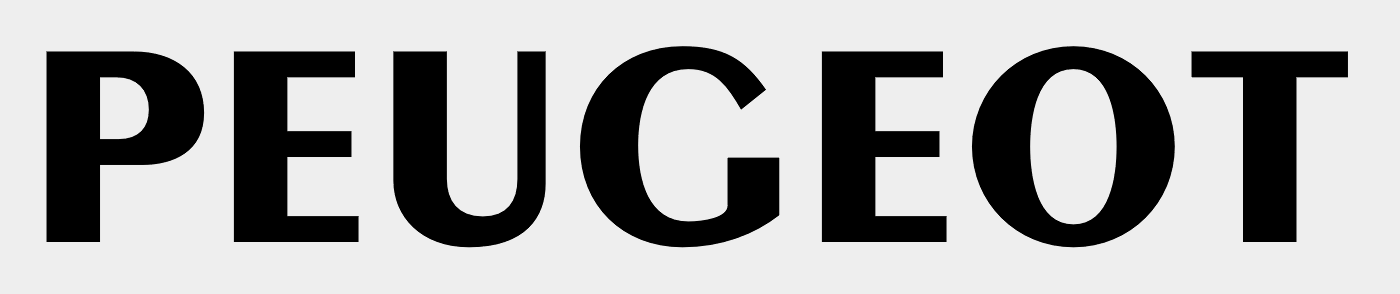
alte Peugeot-Schrift
bin neu hier. Suche diese bestimmte Schriftart, oder zumindest etwas sehr ähnliches.
vielen Dank für den Link. Mache gerade ein Hintergrundbild und ne Navigation für mein TZablet, welches ich in mein Peugeot einbauen möchte. Da kommt das genau richtig. Hatte im Netzt zwar was gefunden, aber die Quali war nicht so gut. Kann ich also gut verwenden. Hab aber leider die Schriftart noch nicht gefunden, die dem Logo ähnelt. Wäre ja schön, wenn die zu dem Logo passen würde.
Und generell wirst du wohl (noch ;-) ) kaum die genaue Schrift finden, denn diese 6 verschiedenen Buchstaben hat der Gestalter des Logos nicht aus einer Schrift entnommen, sondern eben gezeichnet.  So war das damals einfach, als eigentlich nur Bücher, Zeitungen. Zeitschriften, Prospekte, sowie diverse Akzidenzen in Blei gesetzt und auf Papier gedruckt wurden. Alles andere, was Schrift darstellt, wurde dann von Hand gezeichnet oder gemalt.
Erst seit etwa 3 Jahrzehnten hat man überhaupt die Möglichkeit, immer und überall auf vektorisierte Schriften zurückgreifen zu können.
Stimmt schon, ist nicht unähnlich, aber ich hatte das so verstanden, dass eine passende Schrift zu dem Logo zusätzlich gesucht wird und da finde ich die Broadway ja zu amerikanisch ...
Ja "Broadway " hatte ich schon gefunden, aber die ist leider zu dick.